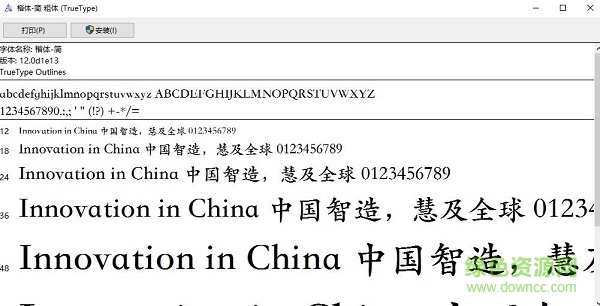
楷體-簡(jiǎn) 粗體是一款生動(dòng)鮮活的中文楷書(shū)字體,橫平豎直,結(jié)構(gòu)規(guī)范統(tǒng)一,整體簡(jiǎn)約美觀,具有獨(dú)特氣質(zhì)的氣質(zhì),閱讀效果極佳,歡迎需要的朋友在本站免費(fèi)下載!
楷書(shū)的萌芽期——秦漢,
楷書(shū)發(fā)展期——魏、晉、南北朝,
楷書(shū)繁榮期——隋、唐、五代,
楷書(shū)守成期——宋、元、明、清。